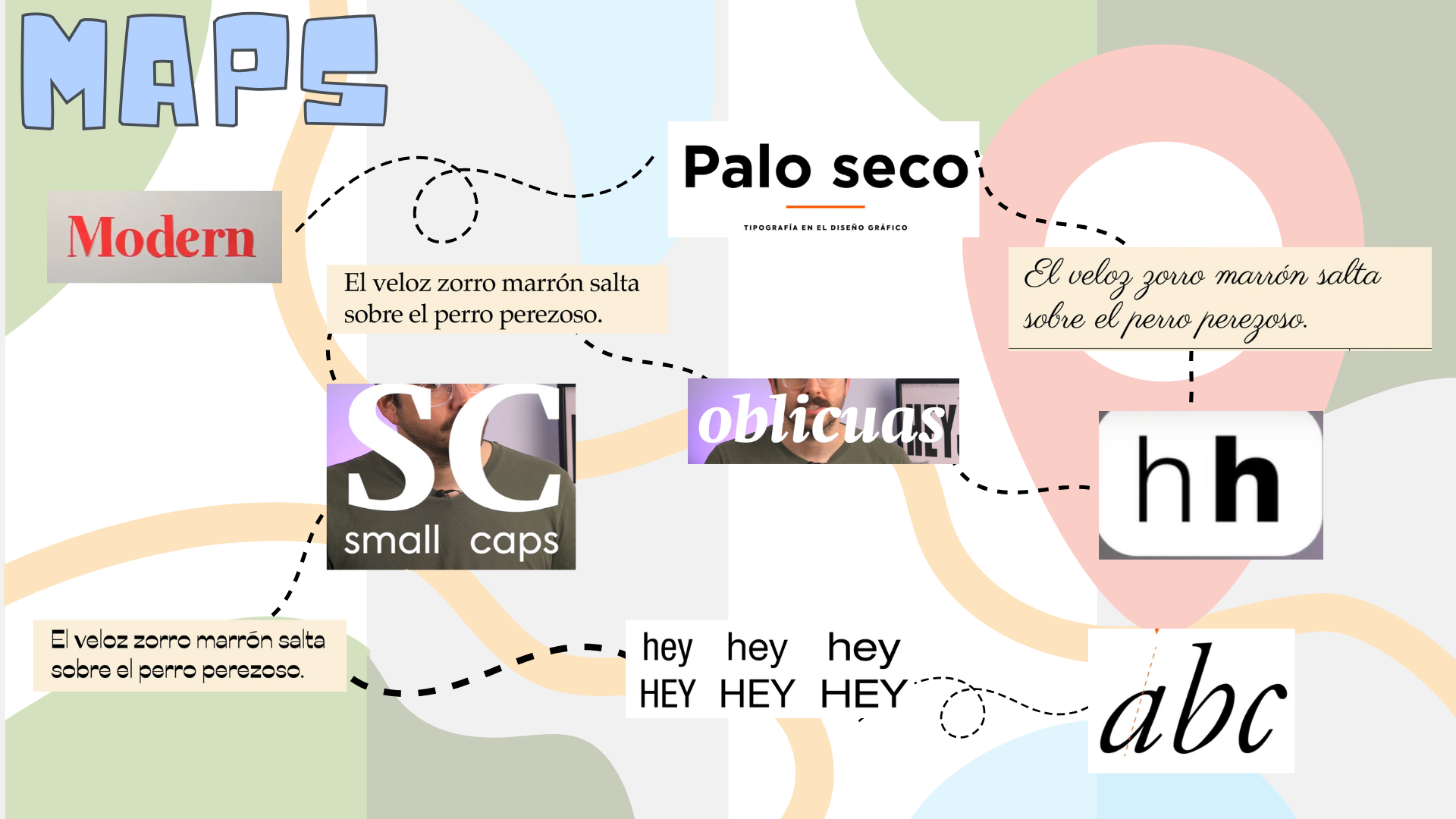
Tipografias
mapa del tesoro tipografica
1 CUAL ES LA TIPOGRAFIA CON SERIFAS 2 CUAL ES LA TIPOGRAFIA VERSALITA 3 CUAL ES LA VARIABLE TIPOGRAFIA DE PESO 4 CUAL ES LA VARIABLE TIPOGRAFIA DE INCLINACION 5 CUAL ES LA TIPOGRAFIA SIN SERIFAS 6 DIDOT Y BODONI QUE TIPO DE LETRA CREARON 7 CUAL ES LA TIPOGRAFIA MANUSCRITA 8 CUAL ES LA TIPOGRAFIA DECORATIVA 9 CUAL ES LA VARIABLE TIPOGRAFIA DE ANCHO 10 CUAL ES LA TIPOGRAFIA ADOBE GARAMOND ITALICA